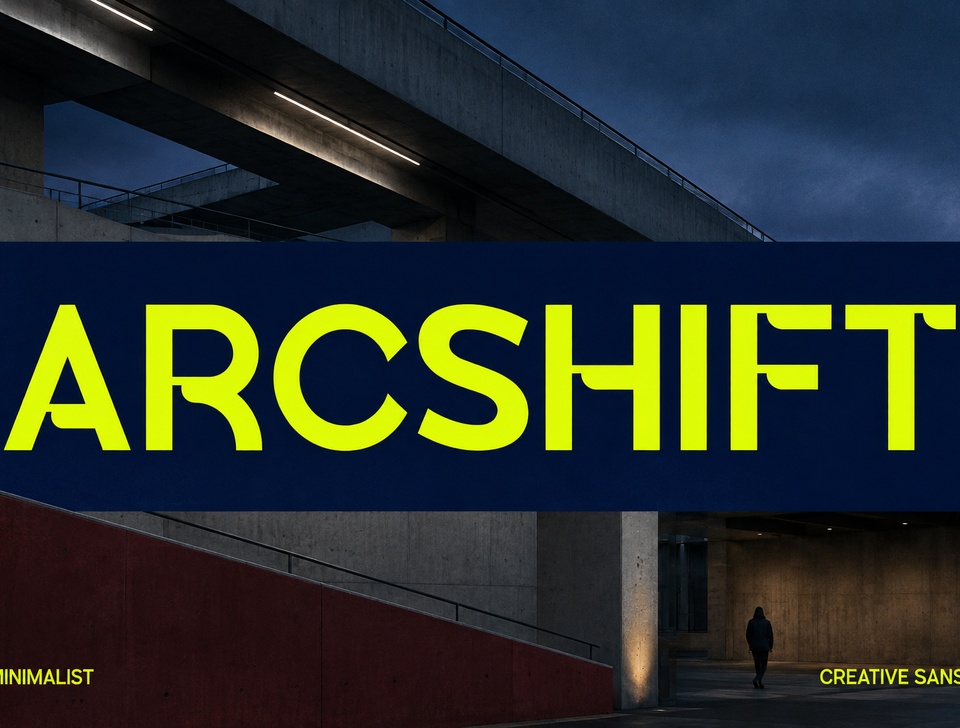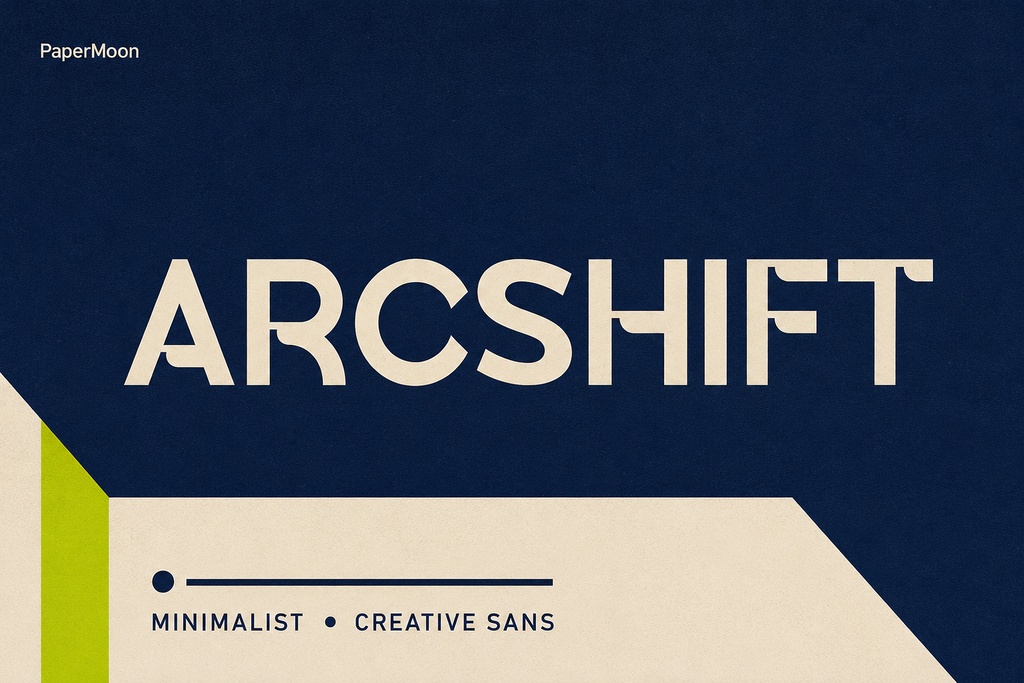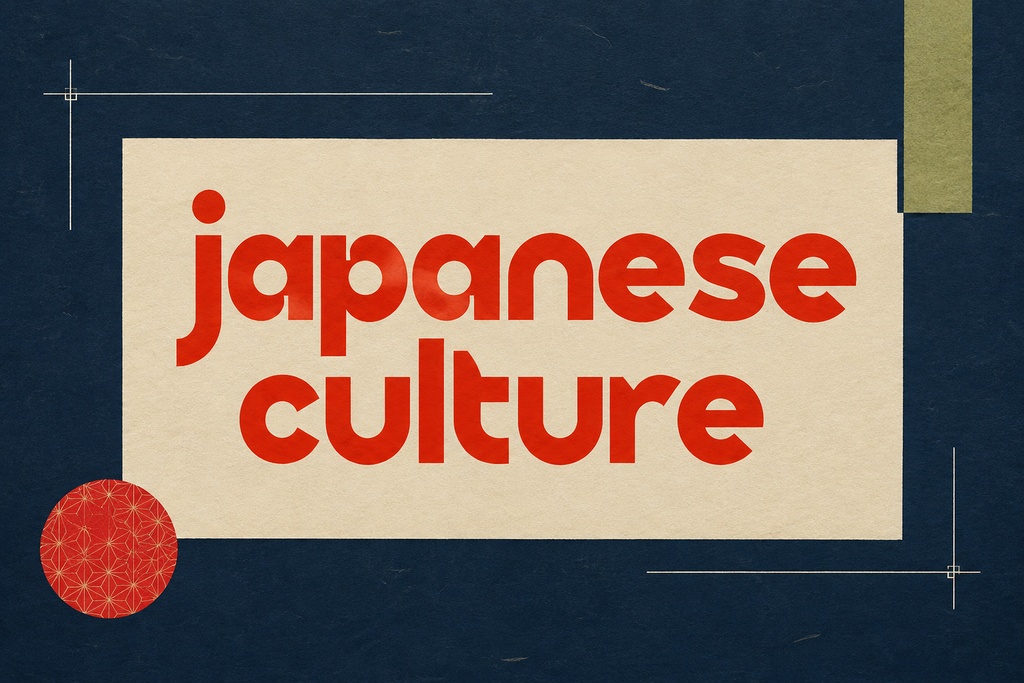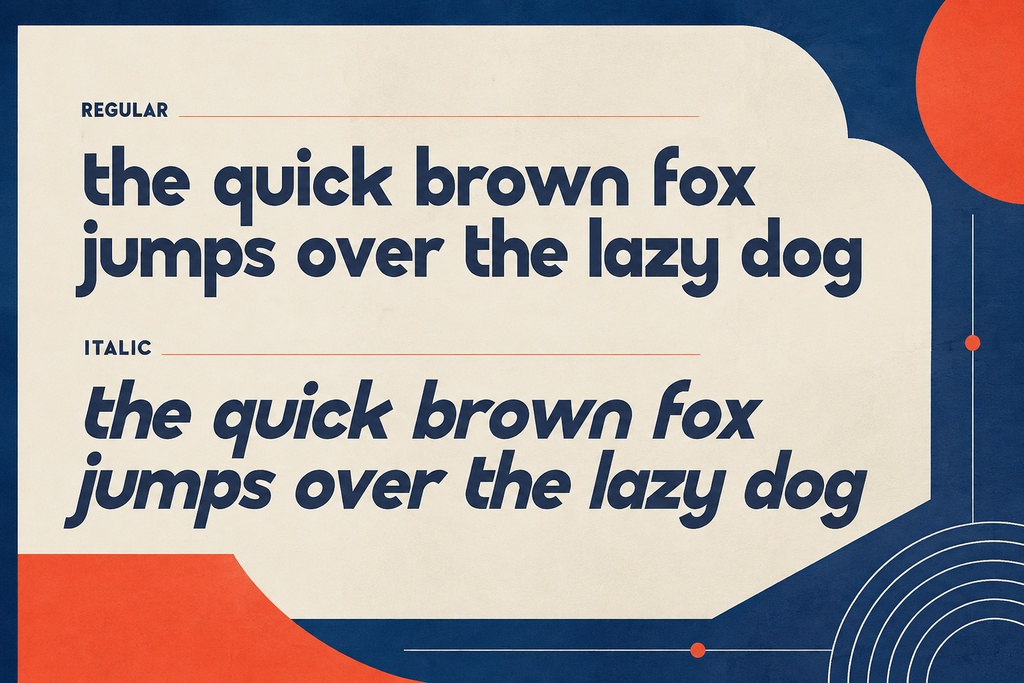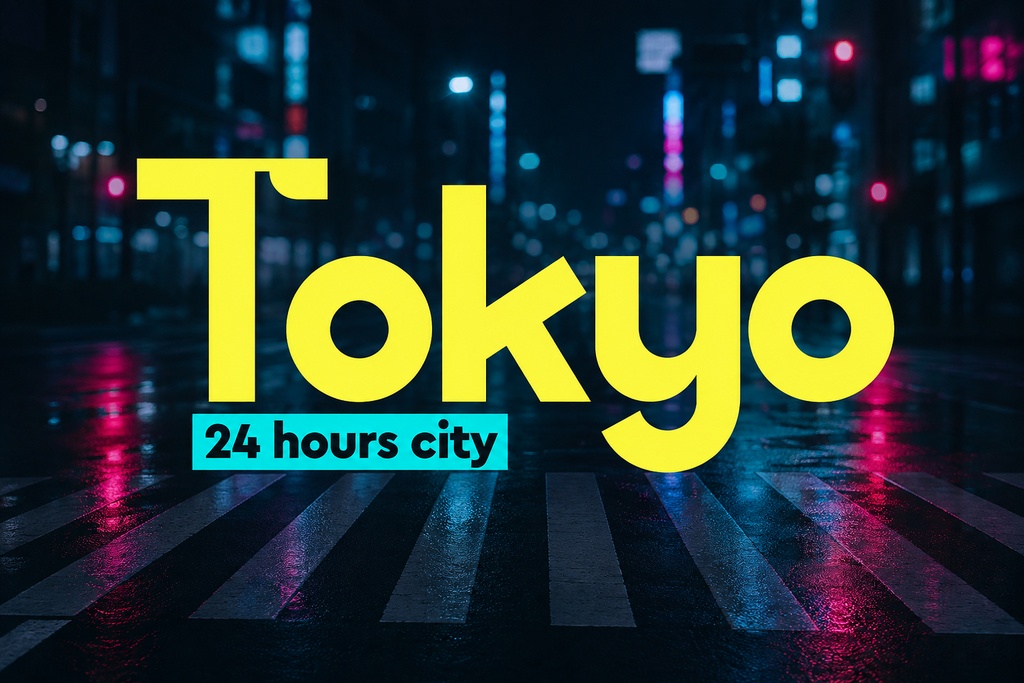
Arcshift — モダンサンセリフフォントデュオ
Arcshiftは、クリーンなライン、バランスの取れたプロポーション、そして現代的でプロフェッショナルな印象を備えた、洗練されたモダン・サンセリフフォントのデュオです。Regularスタイルは、明快で安定感のあるタイポグラフィを提供し、Italicスタイルは、強調、見出し、方向性を持たせたビジュアルシステムに適した、さりげない前向きの動きを加えます。このモダンフォントは、ブランディング、Webデザイン、エディトリアルレイアウト、コーポレートアイデンティティ、プロダクトロゴ、ウェディングカードのロゴ、アパレルブランド、パッケージ、ポスター、現代的なディスプレイグラフィックなど、幅広いデザイン用途に対応します。 **収録内容:** * Arcshift Regular:OTF、TTF、WOFF、WOFF2形式 * Arcshift Italic:OTF、TTF、WOFF、WOFF2形式 各スタイルには170個のグリフと171個のマッピング済み文字が収録されています。Basic LatinおよびLatin-1の文字、アクセント付き文字に対応しています。Cyrillic(キリル文字)、Greek(ギリシャ文字)、その他の広範な多言語文字には対応していませんので、ご購入前に文字セットをご確認ください。本パッケージはPaperMoonによる商用Proリリースで、印刷、デスクトップ、Web制作などの実用的なワークフロー向けに制作されています。 **主な特徴:** Arcshiftには、`liga`機能による標準OpenTypeリガチャと、`kern`機能による文字間隔の調整機能が搭載されています。これらの検証済み機能により、OpenTypeコントロールに対応したアプリケーションで、より滑らかで整った文字組みを実現できます。 本パッケージには、検証済みのスタイル代替文字、スワッシュ、オーナメント、代替文字セットは含まれていません。 Regularフォントは、明快なワードマーク、企業向けコミュニケーション、インターフェースの見出し、エディトリアルテキストなどに適しています。Italicフォントは、コントラストを加えたいデザイン、補足キャプション、キャンペーンフレーズ、コールアウト、躍動感のあるブランド表現などにおすすめです。 **用途:** このクリーンなサンセリフフォントは、ブランディングフォント、ロゴフォント、エディトリアルフォント、Webフォント、プロフェッショナルなディスプレイ書体として使用できます。 テクノロジースタートアップ、プロダクトアイデンティティ、企業プレゼンテーション、デジタルインターフェース、オンラインポートフォリオ、雑誌の見出し、ファッション・アパレルブランド、ウェディングカードのロゴ、パッケージ、ポスター、SNS用グラフィック、マーケティングキャンペーンなど、さまざまな用途に適しています。 バランスの取れたデザイン構造により、短いディスプレイテキストでもシャープで読みやすく仕上がり、Italicスタイルと組み合わせることで、実用的な2スタイルのフォントシステムとして活用できます。 **互換性:** OTFまたはTTFファイルをWindowsまたはmacOSにインストールすることで、Adobe Photoshop、Illustrator、InDesign、Microsoft Word、Canva、Procreate、Figma、Affinityシリーズ、Cricut Design Space、Silhouette Studioなど、対応する各種ソフトウェアで使用できます。 WebサイトやWebプロジェクトでは、適切なCSSの`@font-face`設定を使用してWOFFまたはWOFF2形式をご利用いただけます。 ダウンロードには、PaperMoonの商用Proパッケージとして、2スタイルのフォントデュオ全体と、記載されている4種類すべてのフォーマットが含まれています。 **ライセンス:** クライアントワーク、有料ブランディング、マーケティング、デジタル製品、物理製品、その他の商用プロジェクトには、Cubebrush Commercial Licenseを選択してください。 商用利用には、フォントファイルを単独のアセットとして再配布、再販売、共有することは含まれません。 Basicライセンスは、アップローダーでそのオプションが利用可能な場合に限り、個人利用および非商用プロジェクトにのみご利用ください。 ダウンロードに付属するライセンス条件を必ず遵守してください。 次のアイデンティティシステムに、精密で現代的な表現力を加えましょう。 Arcshiftをカートに追加して、幅広いデザインに対応できるモダン・サンセリフフォントデュオで、新しいデザインを始めましょう。